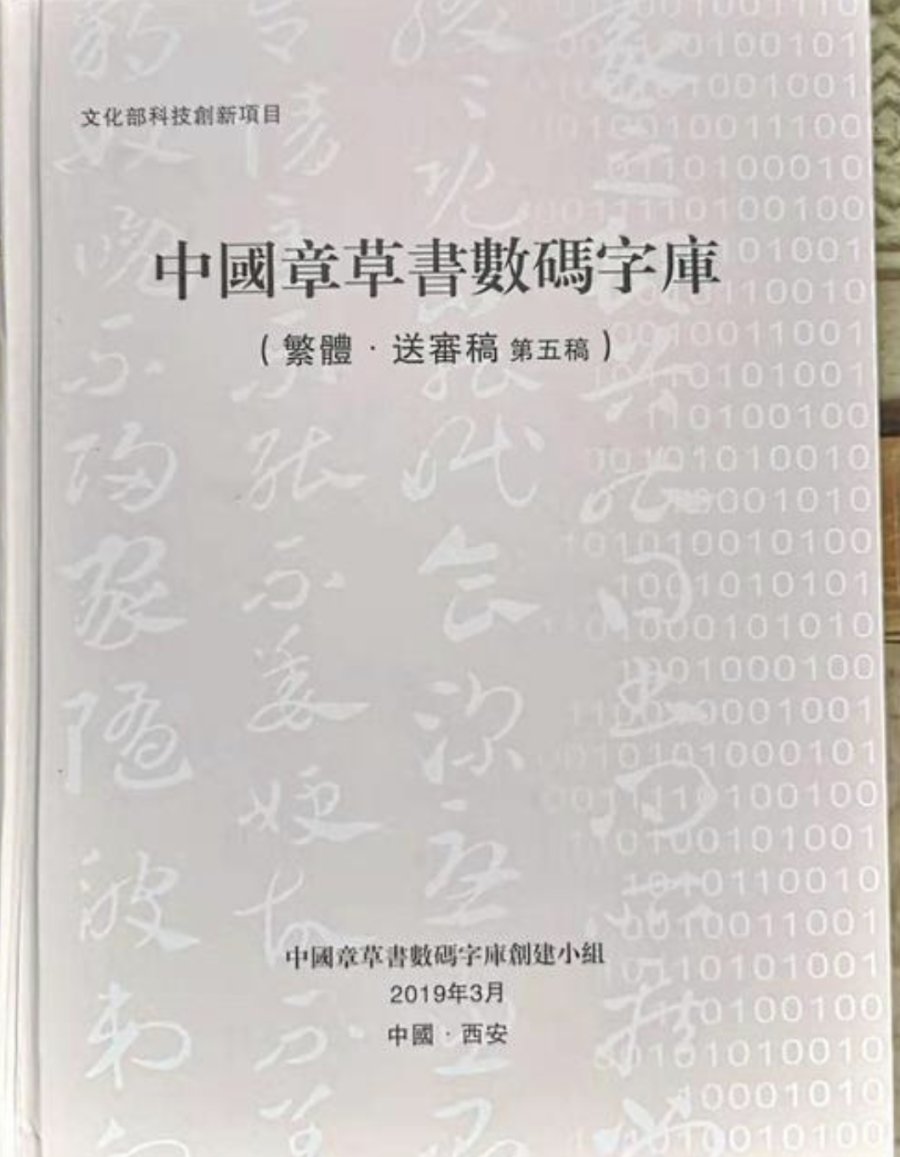
作为原文化部2015年度立项的科技创新项目之一,由陕西书学院申报承担的“中国章草书数码字库创建及其推广应用”项目近日通过评审验收并准予结项。作为我国又一项重点文化科技创新研究成果,该项目将历史遗存的仅有2000个单字的章草书,丰富到6825个单字,使章草书作为独立书体和完整字库,实现了与微软操作系统以及汉字激光照排系统的对接,为中文计算机字库增加了新的字体。
章草作为一种书体,上承篆隶,始创于西汉,是隶书的快捷写法,也是东汉和魏晋时期通行的一种重要书体。作为草书之祖,章草又被称为中国书法的活化石。该项目依据中国文字和中国书法发展史中与章草书体和章草书法文化相关的所有文献资料,以王世镗的《章草草诀歌》《稿诀集字》为法则,以《章草大典》《章草字典》为基本参照,按照国标GB2312字库的要求和“六书”的造字规则以及书写的自然自由性逐一书写字模,然后通过扫描、录入、矢量、质检、测试、转化等环节工作,最后形成了章草书字库。该项目成果的特色在于实现了文化典籍资源的数字化转换,是一种颇具时代感的文化实践。
本项目由国家一级美术师、书法文化工作者卫高潮负责。他表示,中国章草书数码字库的建成,实现了对最早、最古朴、最规范的草书体系的系统性整理,而利用计算机图像处理及仿真技术挖掘章草书法文化价值,进一步拓宽了艺术设计的空间,丰富了书法学习和研究的模式,拓宽了章草书法实际推广应用的渠道。根据评审验收意见,申报单位将对字库进行全面微调,预计明年上半年出版发行并上线运行。
据了解,目前我国中文计算机字体行业发展相对比较滞后。英美现有英文字体数十万种,日本有日文字体近3000种,然而,中国汉字仅有400余种中文计算机字体,书法独立字体系列字库不过二三十种。(记者 秦毅)